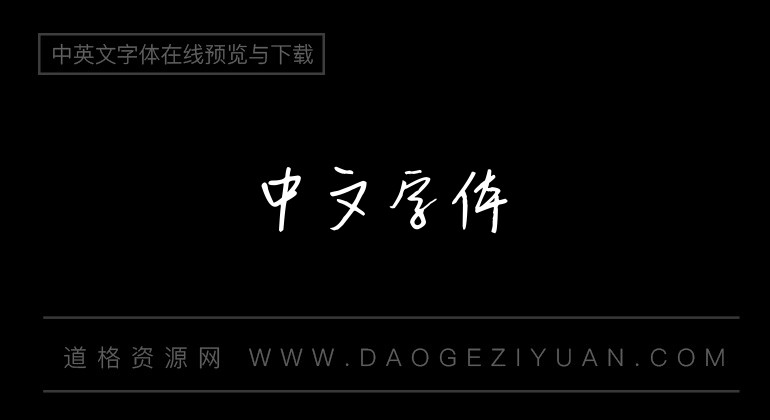
新葉念體
新葉念體是一種新型的漢字字體,由日本設計師葉念介所設計,以古典漢字為基礎,融合日本傳統的折行書法特點,在漢字的結構及筆劃上做了精心的改良,使其具有更好的可讀性和更加流暢的書寫感。新葉念體的字體特點是比較細膩,行距稍窄,字形簡潔,擁有較強的可讀性,適合用於設計中的文字表現,也是很多書籍的專用字體。
新葉念體是一款非常不錯的手寫藝術字體,具有很好的視覺感,適合於文化類的宣傳設計、商業類品牌的廣告和產品包裝設計以及個性化文字排版等較多場景。
新叶念体字符映射图